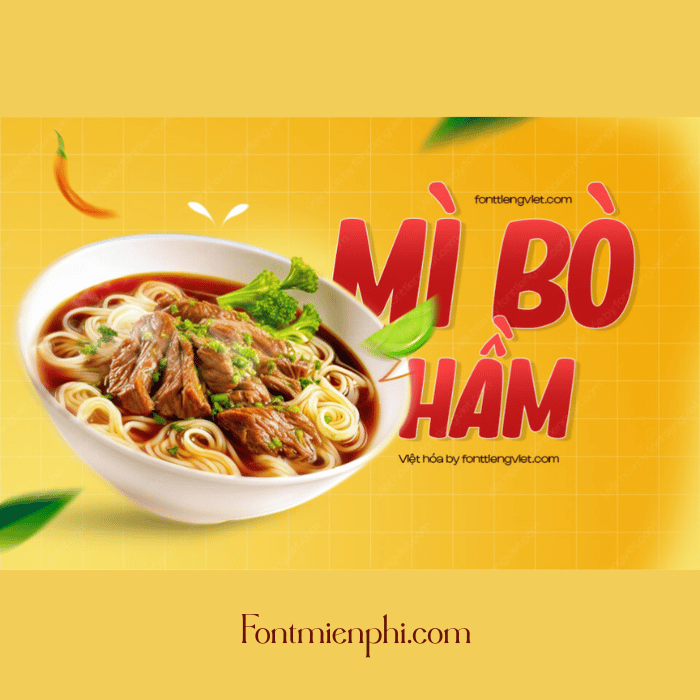
Font Việt hóa 1FTV VIP Magic Dreams
Font Việt hóa 1FTV VIP Magic Dreams – Phong Cách Độc Đáo, Sáng Tạo Không Giới Hạn
Font Việt hóa 1FTV VIP Magic Dreams là bộ font chữ nghệ thuật đẹp mắt, được thiết kế dành riêng cho dân thiết kế, content creator và những ai yêu thích typography. Với nét chữ mềm mại, bay bổng cùng hiệu ứng magic dream độc đáo, font chữ này giúp sản phẩm của bạn trở nên ấn tượng và thu hút hơn bao giờ hết.
Đặc điểm nổi bật:
✔ Nhiều kiểu chữ nghệ thuật – Phù hợp cho poster, logo, banner, thiệp mời.
✔ Dễ dàng tùy chỉnh – Tích hợp sẵn các hiệu ứng đẹp mắt.